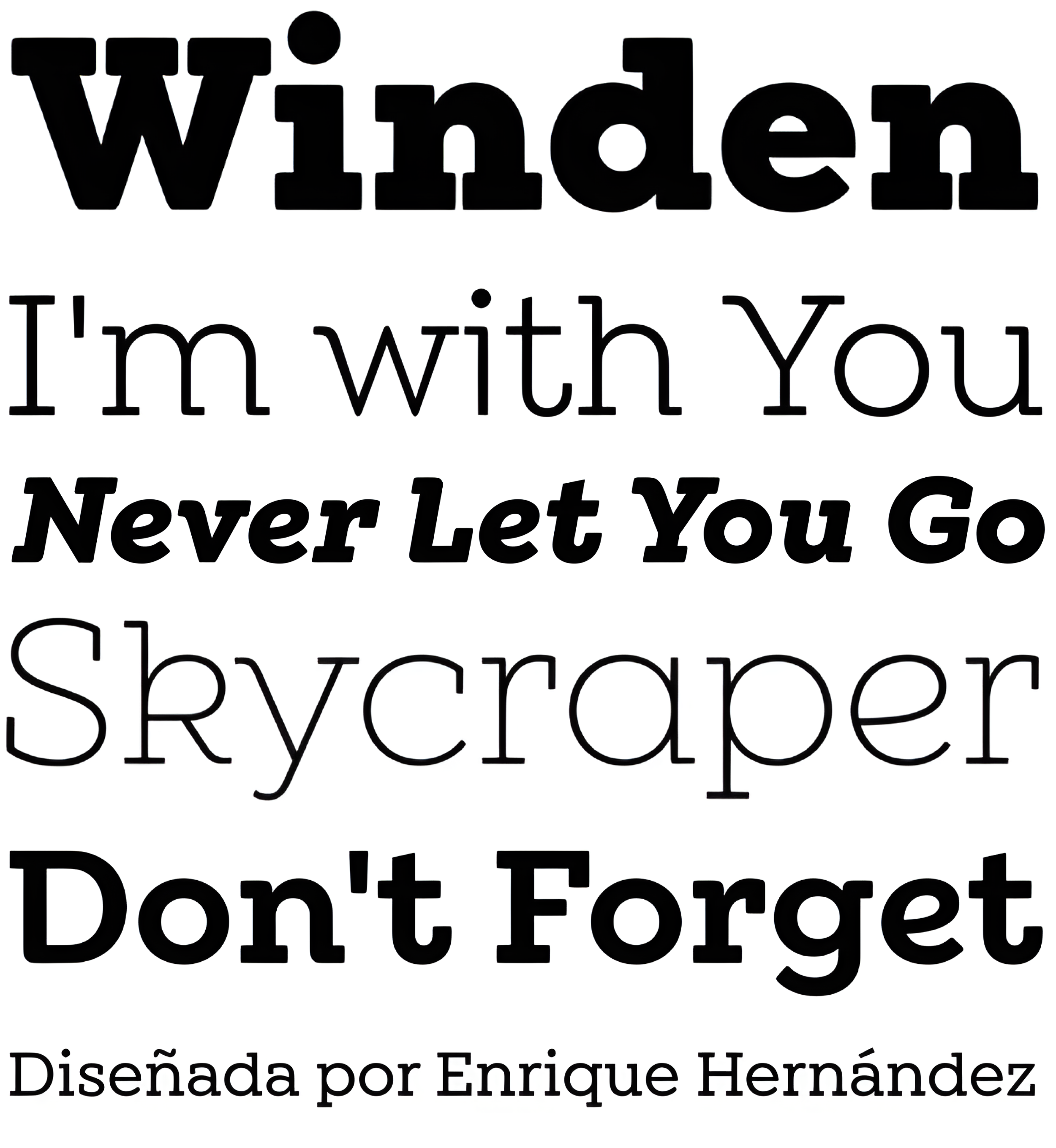
| Año | 2020 |
| Créditos | Enrique Hernández |
| Descripción | Winden es un tipo de letra con gracias geométricas basado en el éxito de ventas Isidora e inspirado en los famosos tipos de letra con gracias clásicas de principios del siglo XX. Rasgos característicos como las gracias trapezoidales dan a Winden un toque moderno y contemporáneo, y los bordes redondeados de la versión Alt le confieren un aspecto único y especial. |
| Familia(s) | Thin, Thin Italic, Light, Light Italic, Regular, Regular Italic, Medium, Medium Italic, Semi Bold, Bold, Bold Italic, Black, Black Italic, Alt Thin, Alt Thin Italic, Alt Light, Alt Light Italic, Alt Regular, Alt Regular Italic, Alt Medium, Alt Medium Italic, Alt Semi Bold, Alt Semi Bold Italic, Alt Bold, Alt Bold Italic, Alt Black, Alt Black Italic |
| Estilos | 28 |